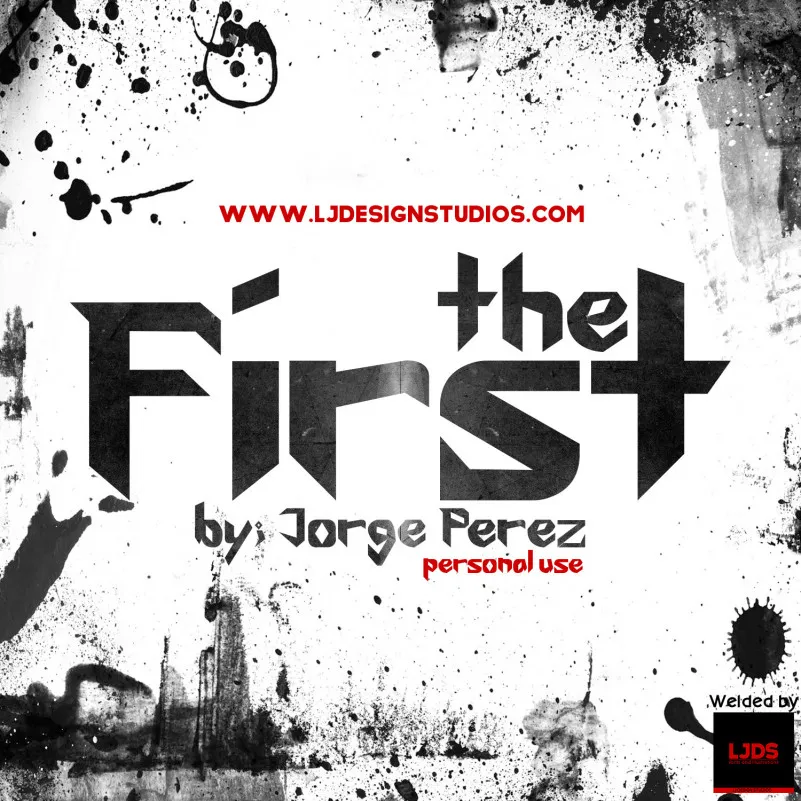
The First Font – Fonte Grátis
The First Font
A fonte The First Font é uma escolha perfeita para quem deseja trazer à vida textos históricos com estilo elegante e arcaico. Inspirada no Blackletter, um sistema de escrita que predominou por séculos na Alemanha, a The First Font captura essa atmosfera rica do passado. Ela foi projetada pelo designer Hamilton para aqueles que buscam uma fonte única, ideal tanto para uso comercial quanto não-comercial. A personalidade distinta e elegante da The First Font faz dela uma escolha ótima para aplicações digitais como livros impressos antigos, menus de restaurante em estilos clássicos ou até mesmo para usar em aplicativos históricos. Se você está procurando por uma fonte que possa trazer um toque distinto a seu projeto, certamente The First Font merece uma atenção especial. Para mais informações sobre o uso comercial desta fonte, visite [LjDesignStudios.com] ou entre em contato diretamente com os responsáveis através dos endereços de email fornecidos.